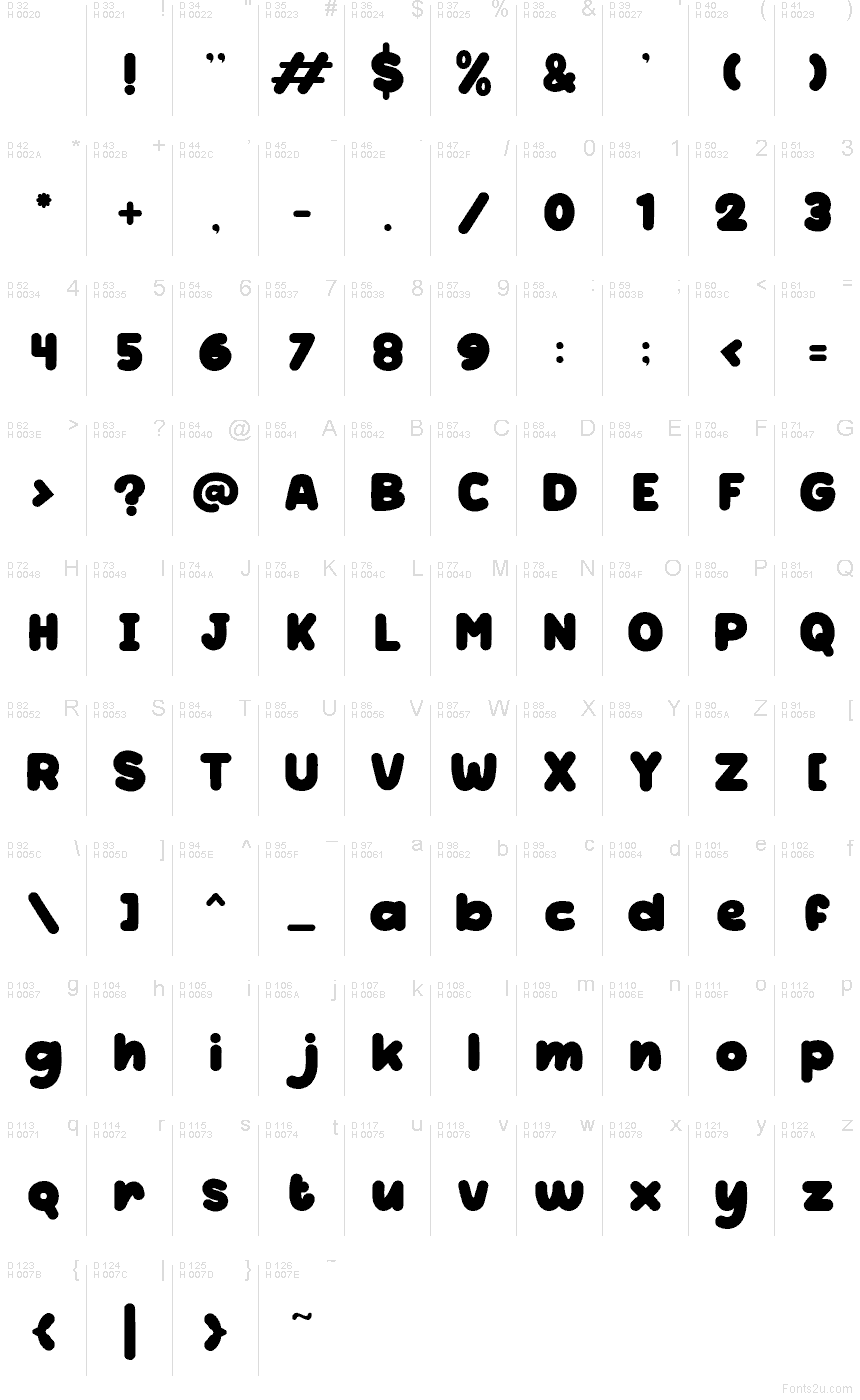
Smoky Maple od Putracetol Studio to darmowy ekranowy font w stylu kreskówkowym o miękkim, pękatym wyglądzie. Litery są grube i przyjazne, mają zaokrąglone rogi i lekko płynny charakter, co nadaje napisom prosty, zabawny rytm, zamiast sztywnej blokowej formy.
Świetnie sprawdza się w projektach opakowań dla dzieci, menu kawiarnianych, naklejkach, grafikach na YouTube i krótkich tytułach, gdzie darmowy krój pisma ma przede wszystkim budować ciepło, a nie perfekcję. Mocne krzywizny i proste sylwetki sprawiają, że jest to również dobry wybór do szkiców logo, zabawnego brandingu i nagłówków, które mają sprawiać wrażenie przytulnych i ręcznie rysowanych, ale bez efektu niechlujnego pisma.
Smoky Maple